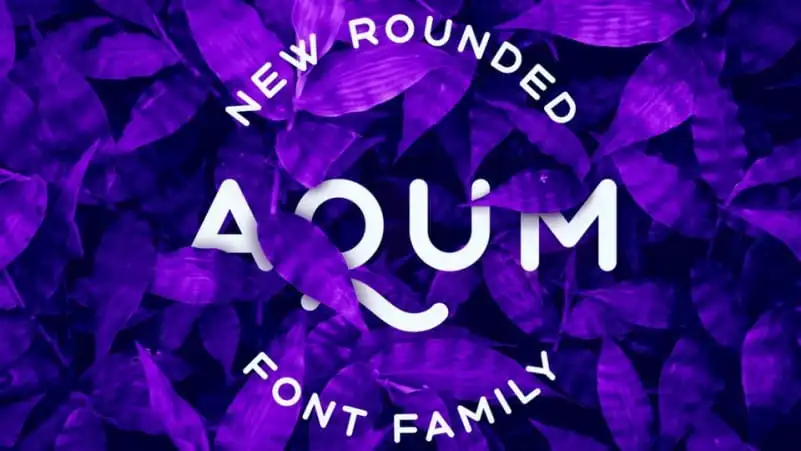
Aqum 2 Sans Serif Font Family – Download Grátis
Aqum 2 Sans Serif é uma elegante e sofisticada fórmula de tipo sans serif que oferece um estilo moderno e classe. Desenvolvida pelo designer Slava Antipov na plataforma de criatividade online 99designs, esta fonte apresenta elementos geométricos arredondados e sua versatilidade é notável para tipos em todas as formas e tamanhos. Com suporte multilinguístico, Aqum 2 não só brilha como headline ou título, mas também se destaca perfeitamente nos documentos, revistas, estampas de roupas e até mesmo nas postagens do seu painel de publicidade. Seja para textos formais ou design visual criativo, a Aqum 2 Sans Serif é uma escolha inteligente que não decepciona.